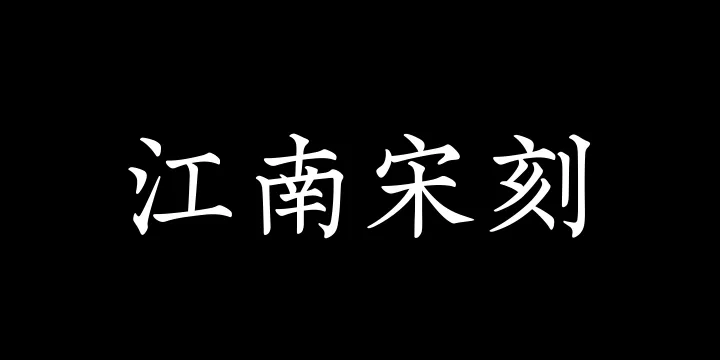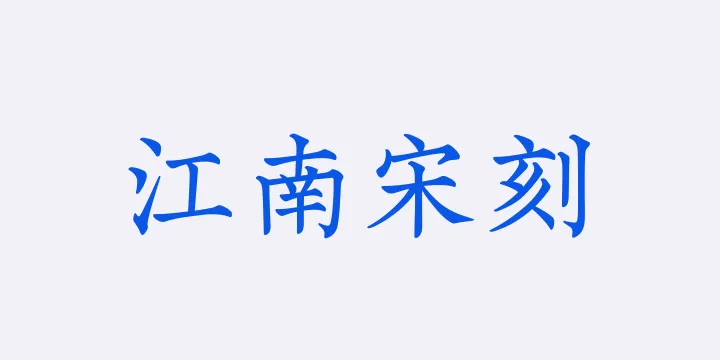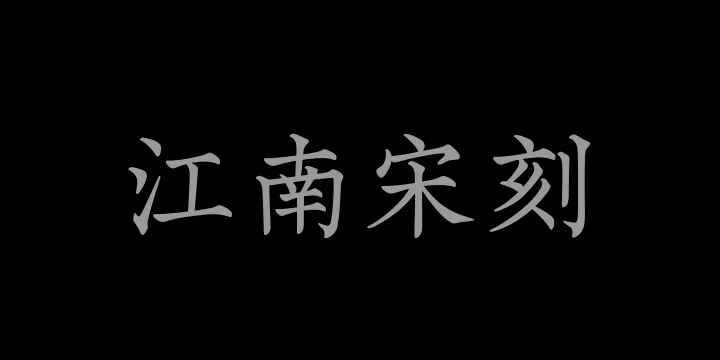
字体全名: 山海汲古江南宋刻W
字体简介: 山海汲古江南宋刻,是一款全新的国风复古刻本字体,包含简繁汉字9169个,符号200+个。字形秉承中国宋代古籍善本之字形特性,字形方正,端庄严谨,古朴大方,起落顿笔有棱角,同时饱有笔墨之意。在秉承笔形间创新,结合当代设计视觉环境,融入现代审美,适用场景更多元,笔画造型清晰锐利,删繁取简,速度感强,重现宋刻本古韵之美。